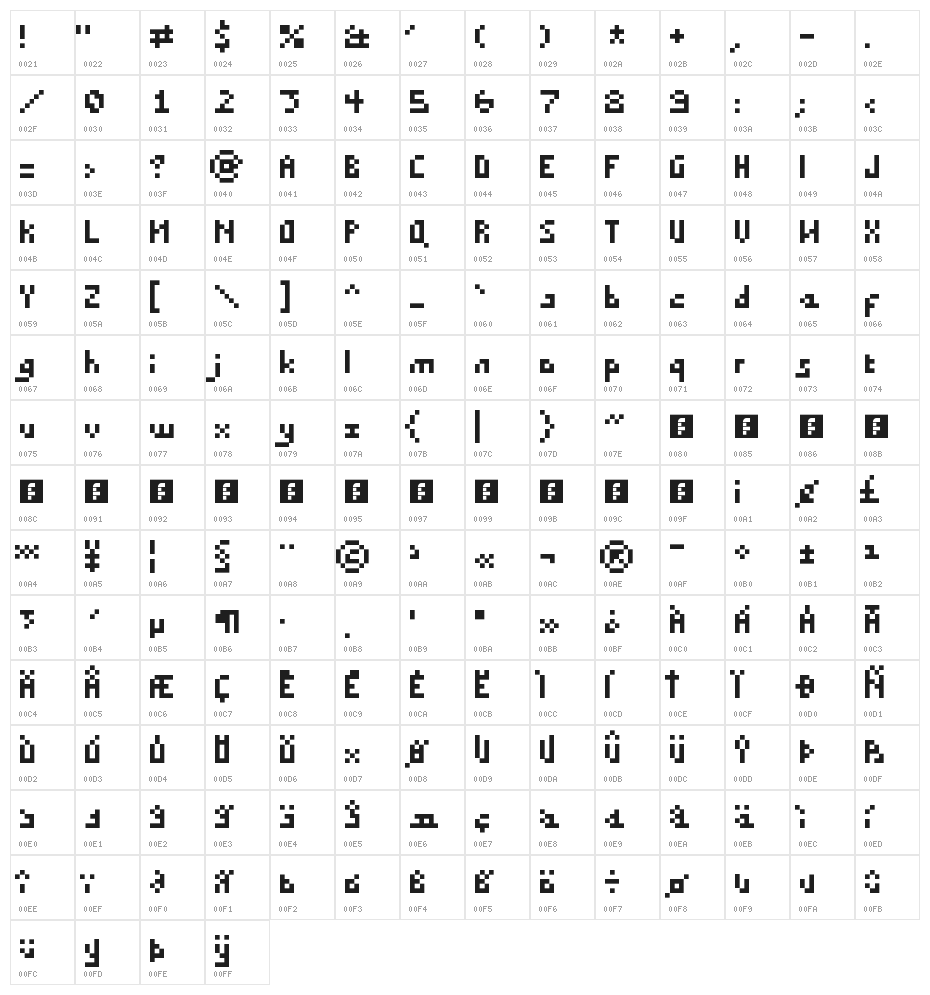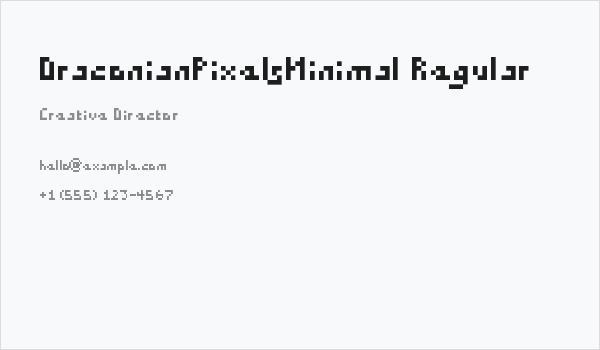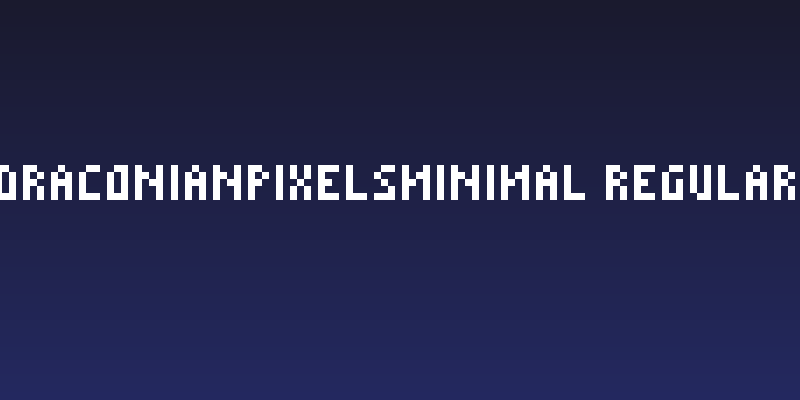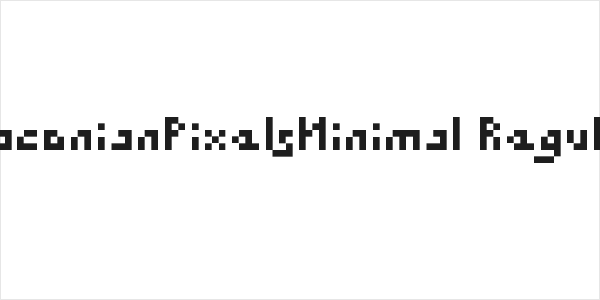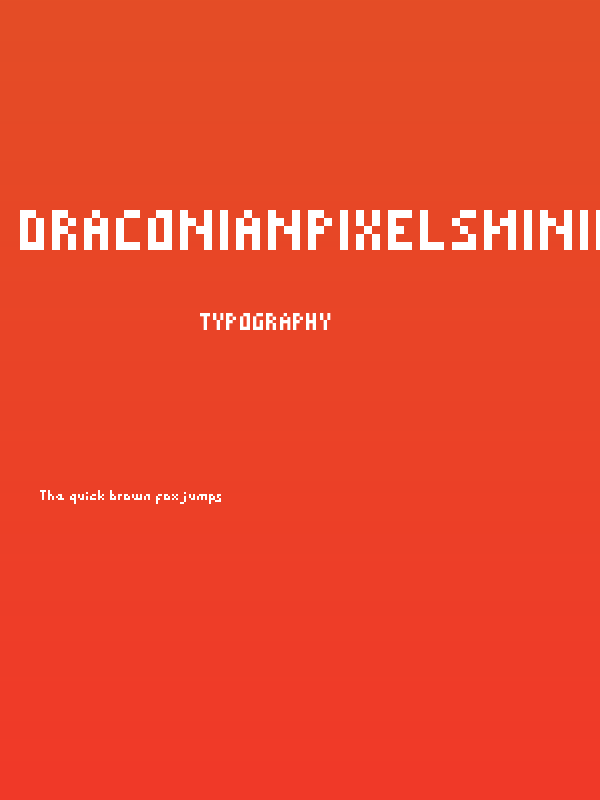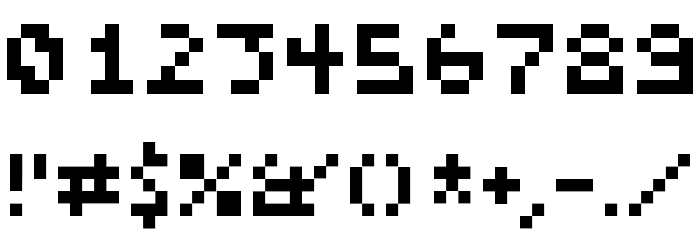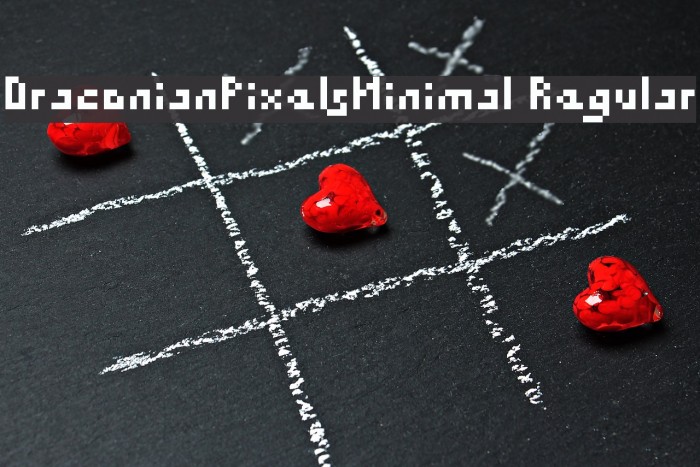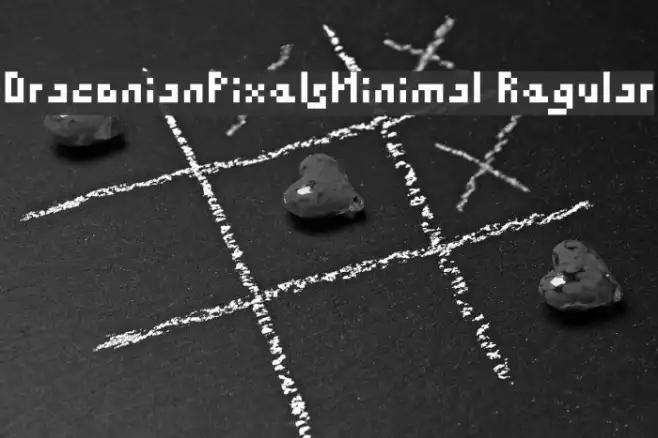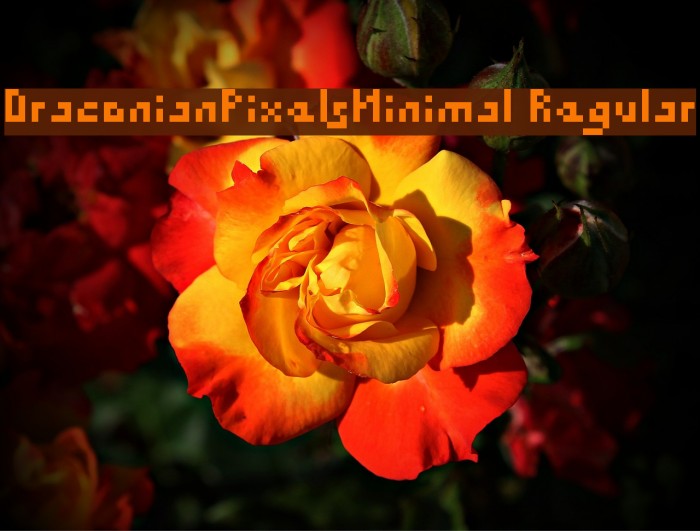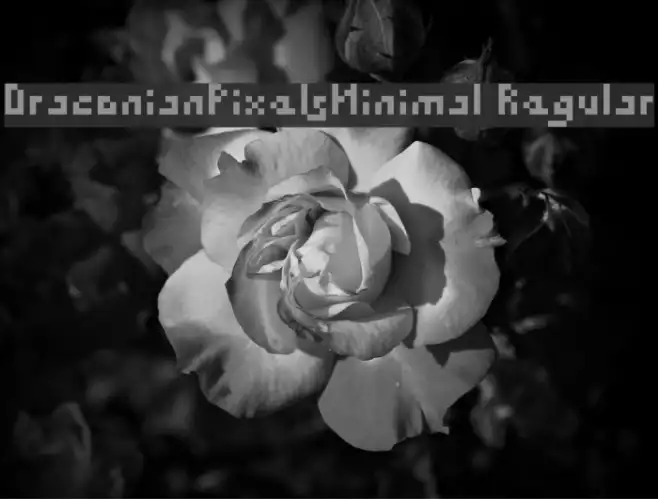
DraconianPixelsMinimal Regular Font
| Categorías | Pixel |
| Estilo general | Vintage |
| Caso de uso | Logos, Headlines, Posters |
| Proyectos propuestos | Ideal for retro video game designs, digital art projects, tech-themed posters, and any creative work that requires a nostalgic digital feel. |